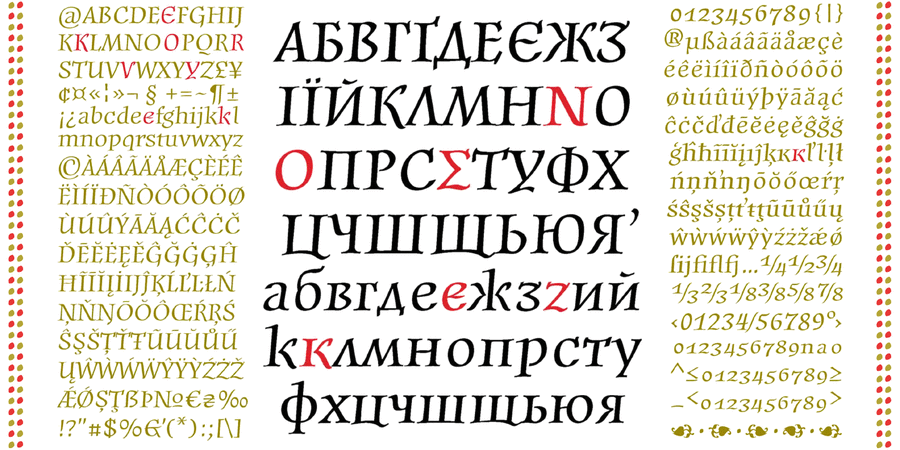
Юрчишин Один – дуже «мистецький» шрифт, зроблений за мотивами каліграфічних літерацій видатного книжкового графика Володимира Юрчишина. Ця вишукана, трохи похилена, незарегульована каліграфічна антиква легко впізнаного «юрчишинського» стилю придатна для оформлення усього, що пов’язано з мистецтвом, літературою, поезією. Вона додає всьому, до чого доторкається, певного ексклюзивного артистичного звучання. Розширений склад латинки та кирилки дозволя набирати тексти майже всіма європейськими мовами, світліше та темніше накреслення збільшують, крім іншого, діапазон можливих уживаних розмірів. Крім суто акцидентних робіт можливо використання в якості непересічної антикви для відповідних за змістом текстів, зокрема поезії. Невелика кількість альтернатив допоможе надати текстові більш чи менш українського та історичного вигляду. Завдяки незамінній допомозі Сергія Ткаченка зґенеровано опентайп-фічи. Шрифт розробили Генадій Заречнюк та Віктор Харик у 2006–2017 роках.
Асоціації з сімейством шрифтів Yurch1Особистість і характер гарнітури:
благородний, консервативний, традиційний, класичний, пафосний, художній, сріблястий, гострий, майстерний, витончений, аристократичний, елітний, якісний, історичний, гуманітарний, срібний, динамічний, осінній, старовинний, казковий, красивий, виразний, характерний, прекрасний, музичний, ритмічний, пластичний, живий, рухливий, розкішний, поетичний, вишуканий, золотий
бібліотека, мистецтво, музей, література, естетика, проза, поезія, музика, геральдика, вино, срібло, осінь, казка, Чарівна казка, комільфо, прикраса, розкіш, живопис, Трофей, нагорода, замок, банкнота, концерт, легенда, цінні папери, графіка, ілюстрація, пейзаж, люкс, пам'ятник, меморіал, золото, монета, туризм Гарнітура має ознаки стилів: